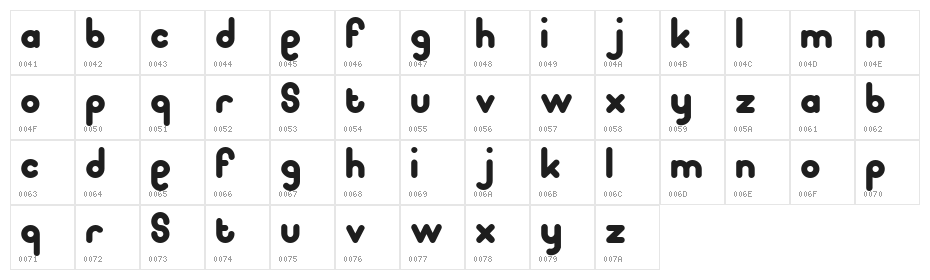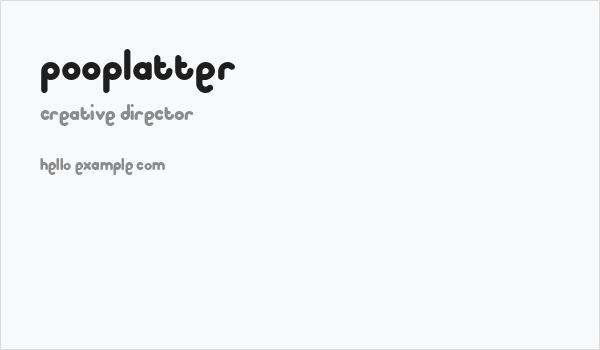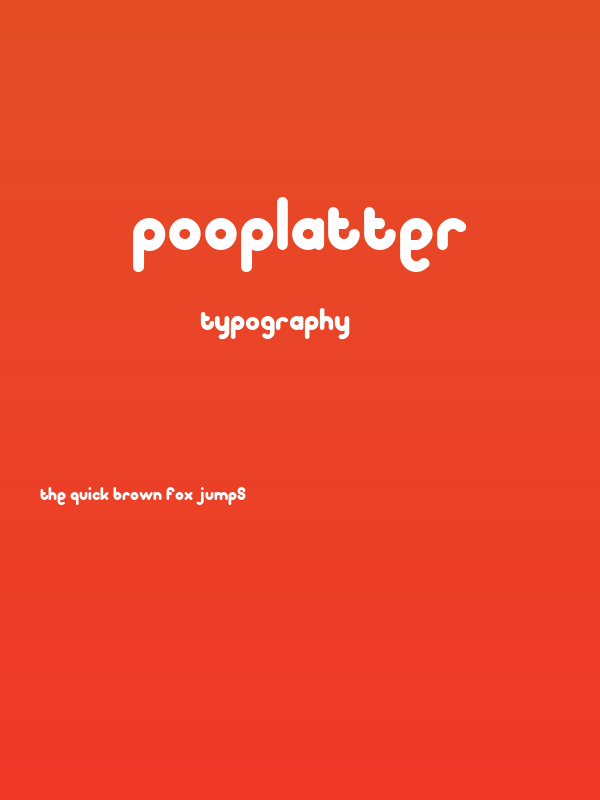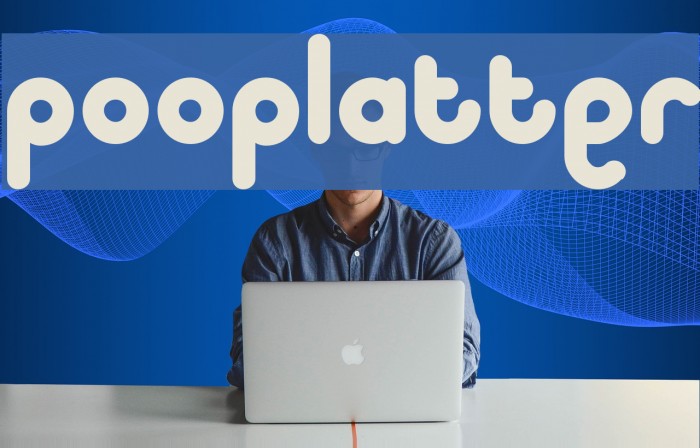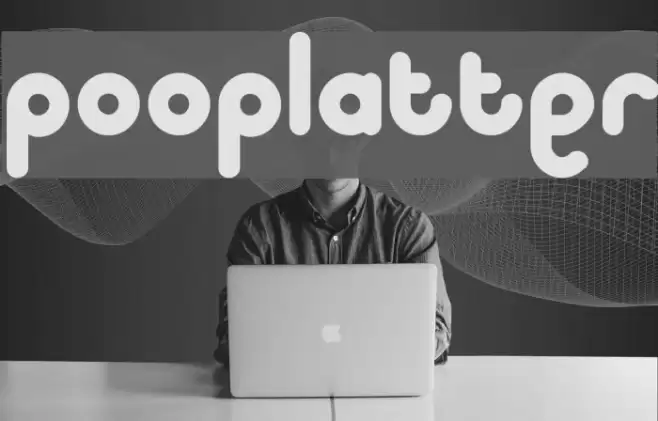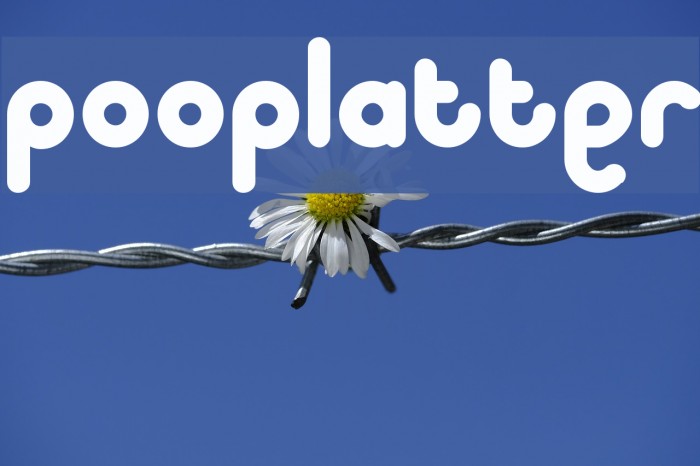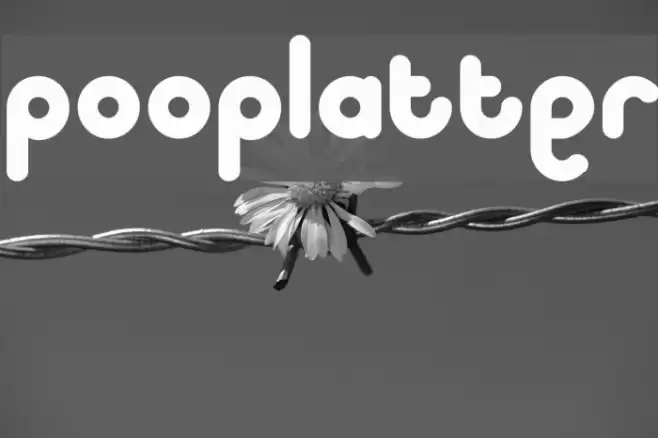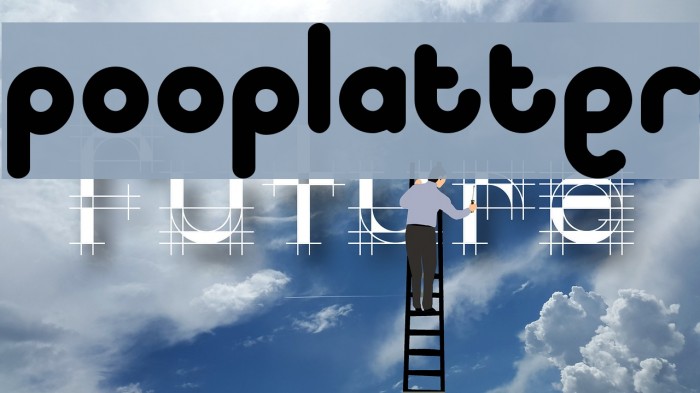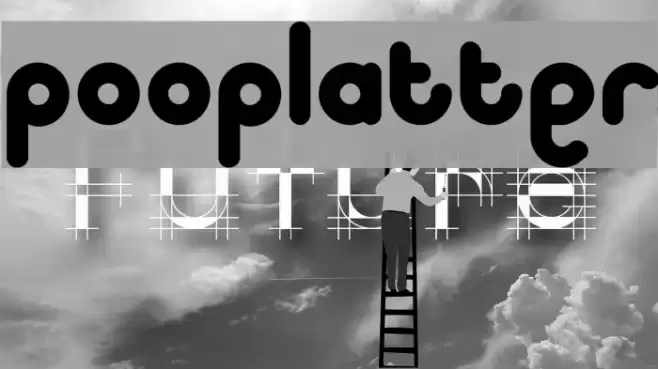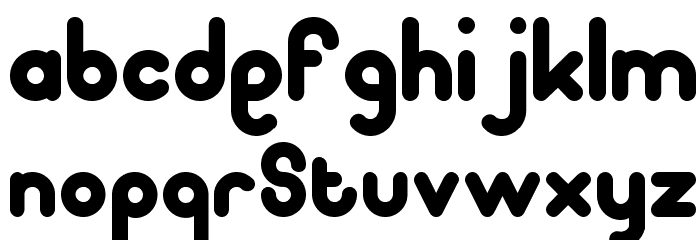
pooplatter Font
| Общий стиль | Playful, Fun, Whimsical |
| Рекомендуемые проекты | Ideal for children's books, playful branding, party invitations, and creative posters. |